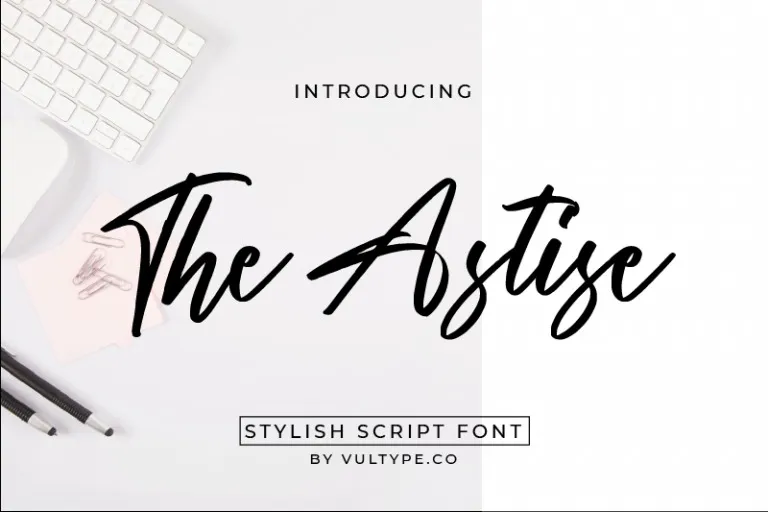
The Astise Font – Download Grátis
A fonte Astise é uma opção irresistível para quem busca uma sensação natural e elegante, perfeita para projetos que exigem delicadeza. Criada pela grandefonts, a Astise possui um traçado cuidadosamente desenhado a mão, conferindo-lhe um aspecto quase autêntico. Ela se destaca especialmente em design fotográfico, embalagens de produto e em eventos especiais, oferecendo uma textura suave que complementa qualquer projeto com delicadeza e elegância. Este tipo-fonte perfeito para designers que buscam personalidade e sofisticação em suas criações. A Astise é uma escolha ideal para aqueles que desejam dar um toque único a seus projetos gráficos, sejam eles para fins pessoais ou profissionais.